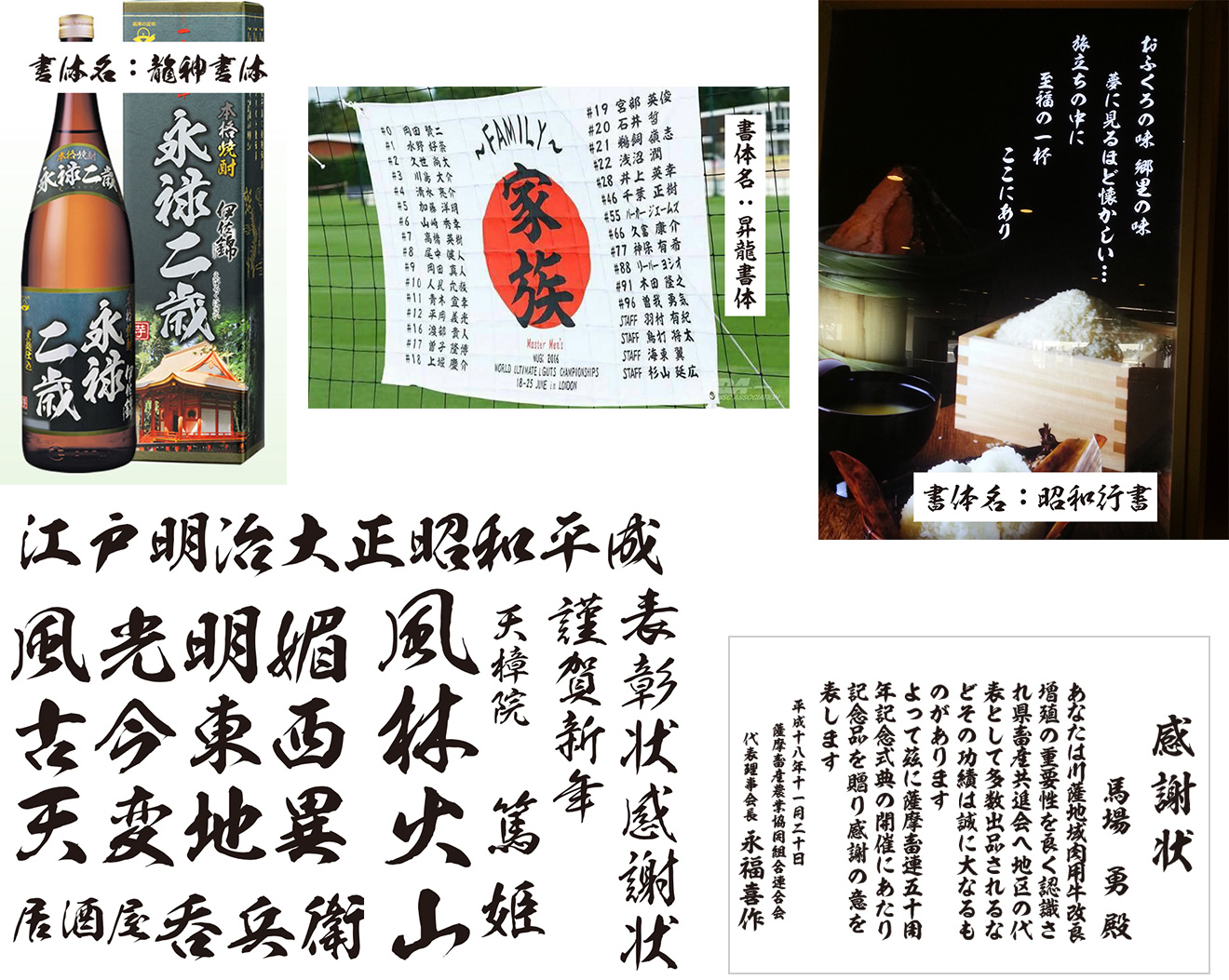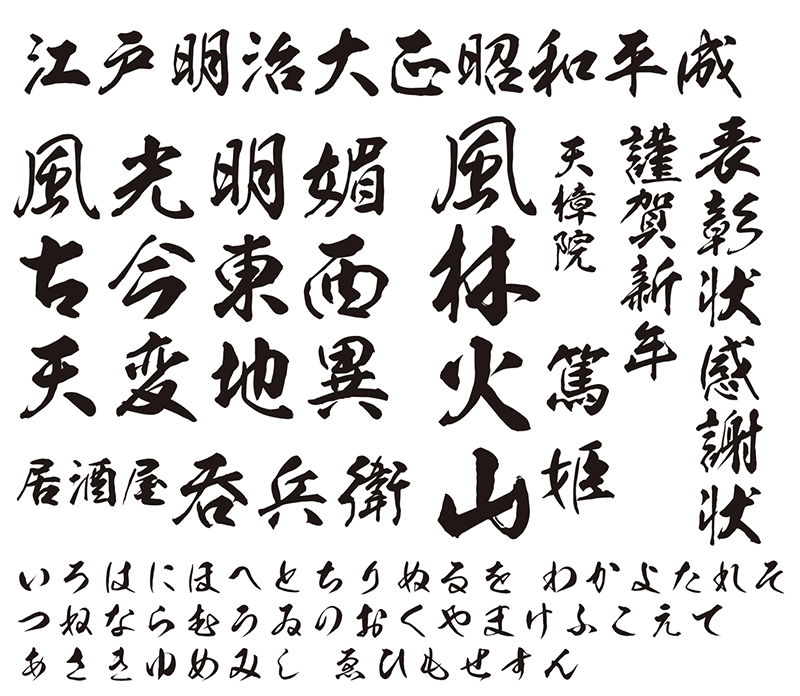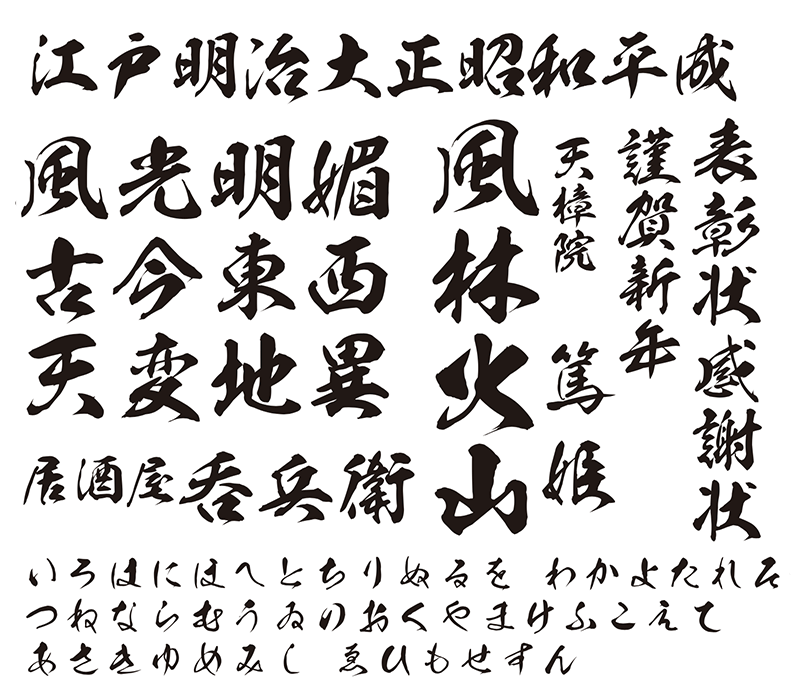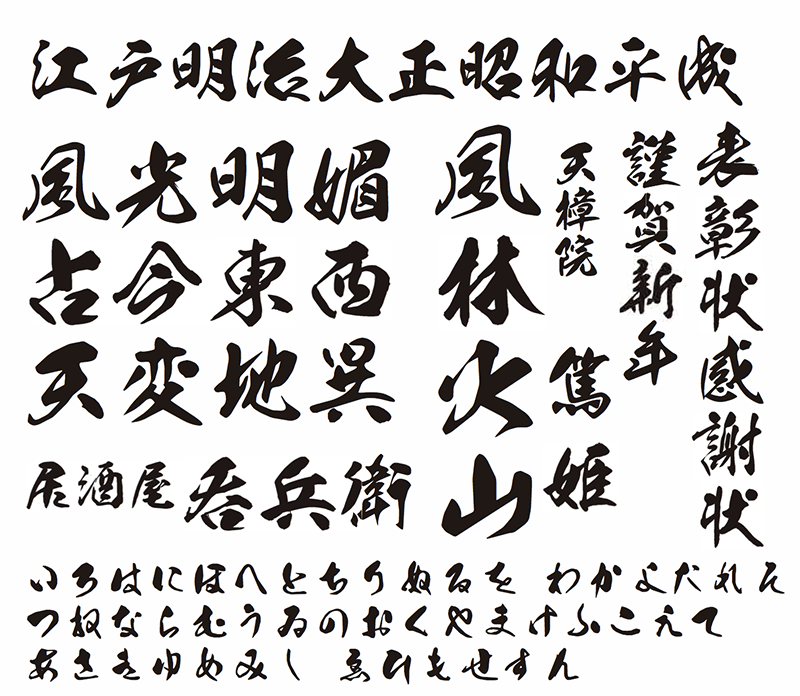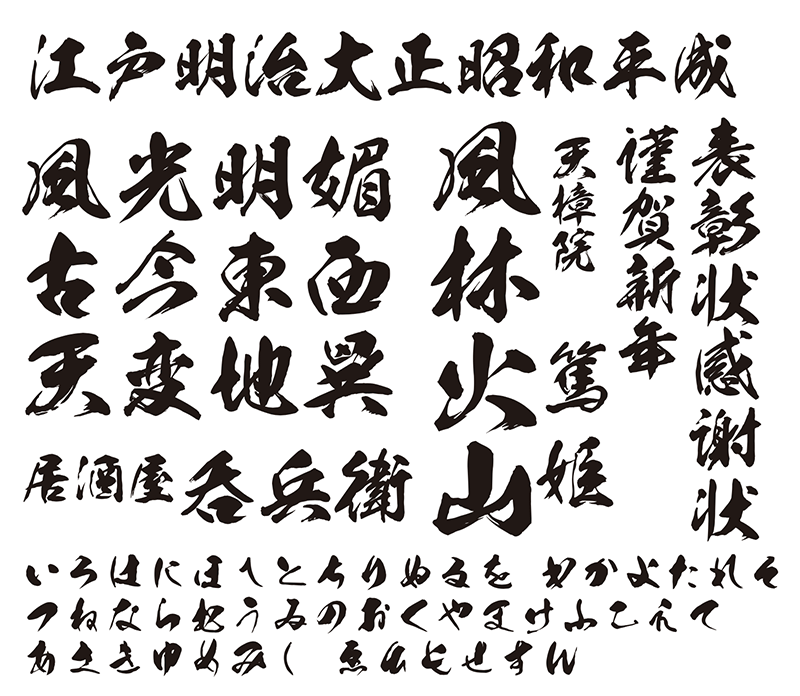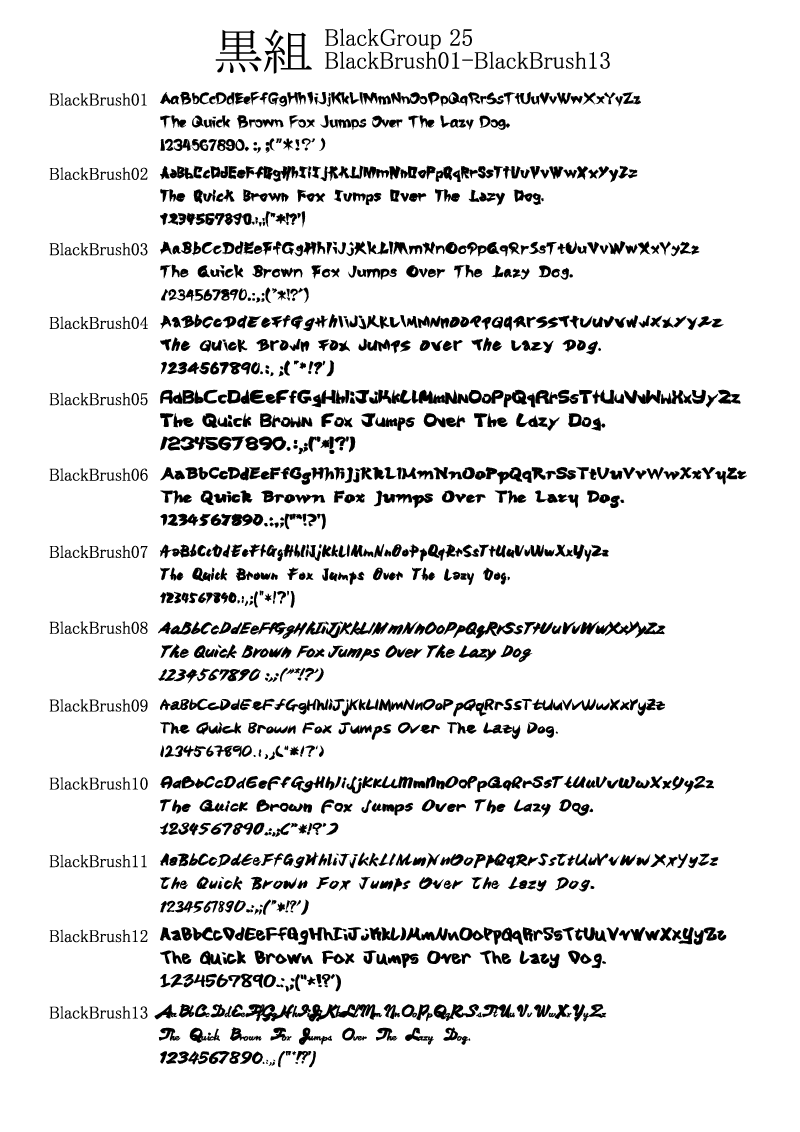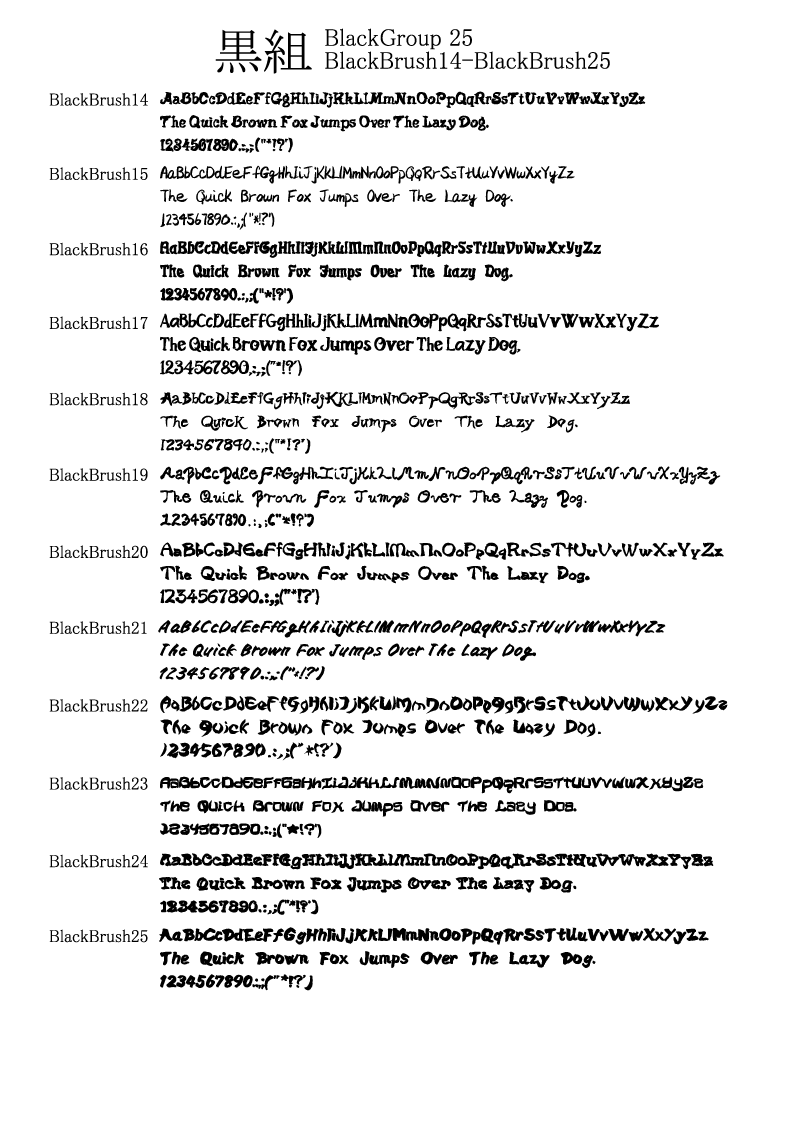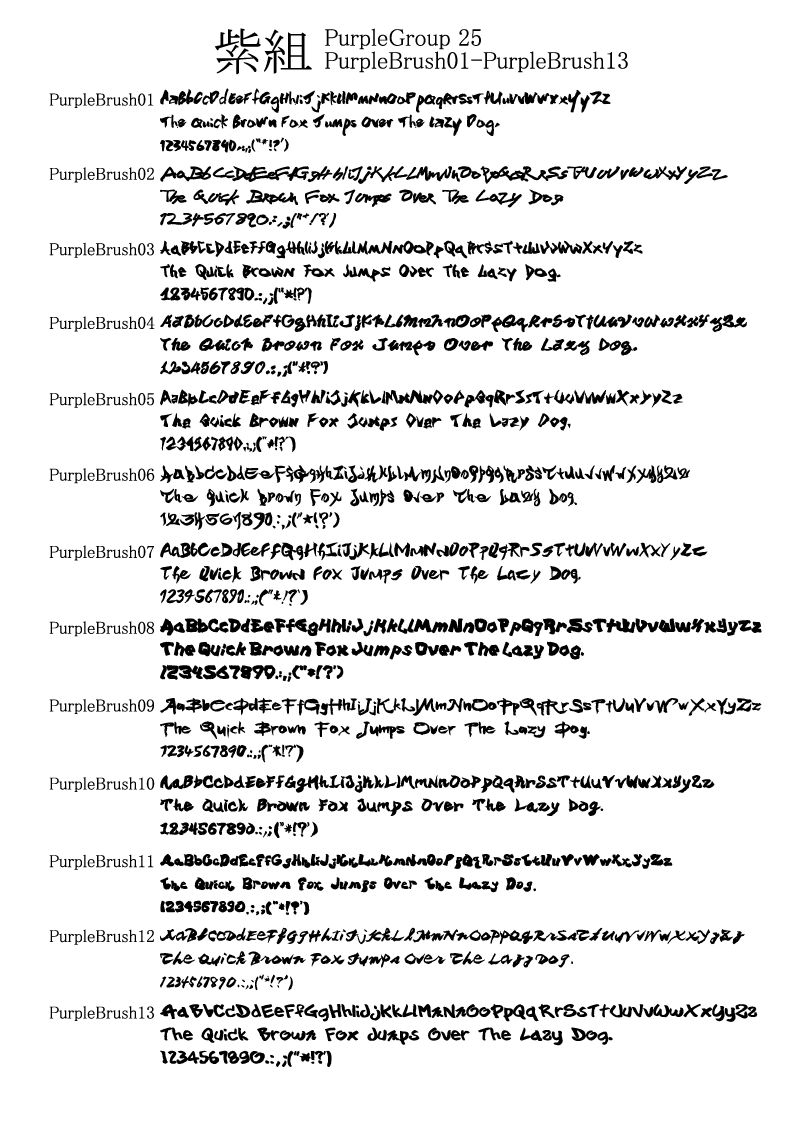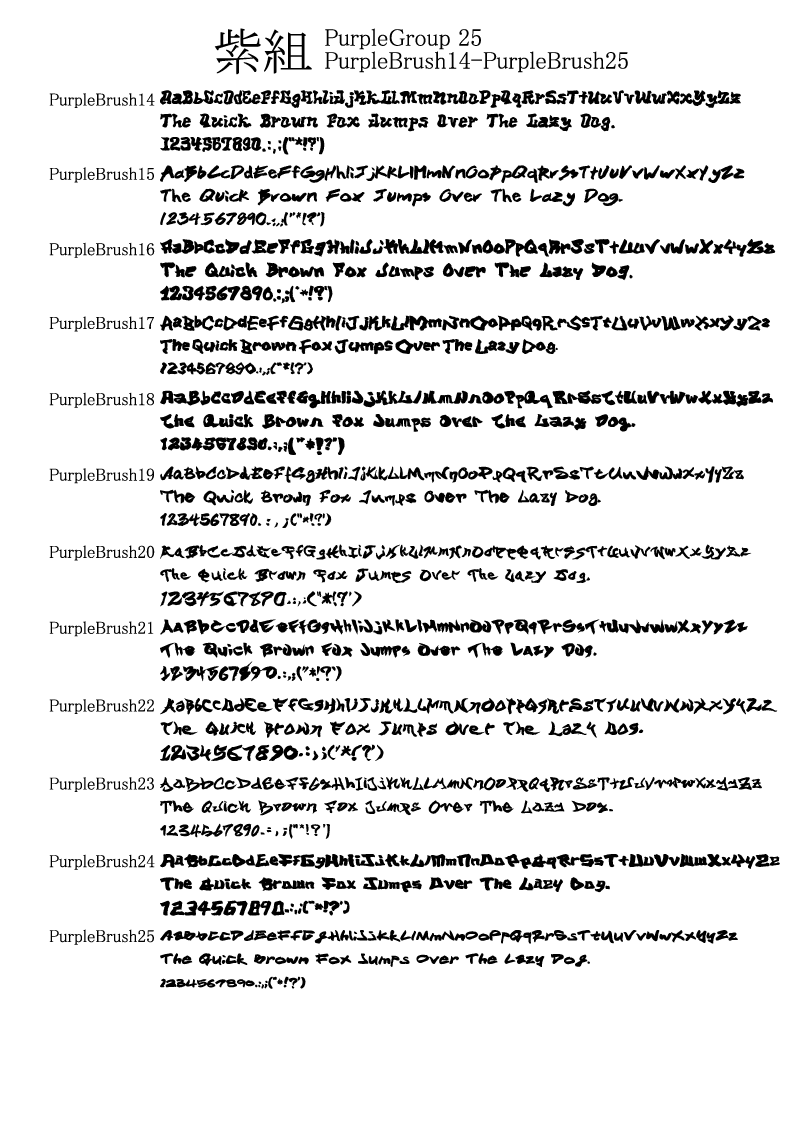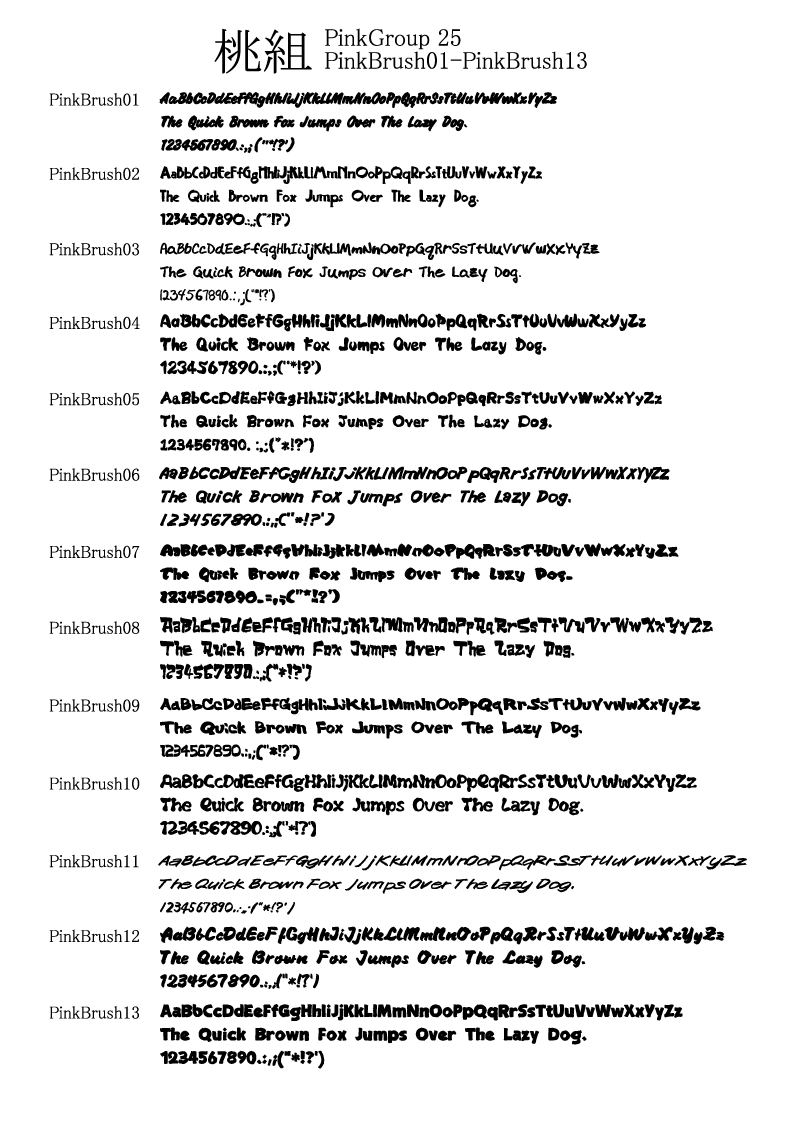
あの人気の筆文字ブランドの昭和書体がFANセレクションシリーズとして製品化。
昭和書体セレクト
昭和書体の基本9書体から2書体をセレクト利用できます。(※クリックで拡大)
昭和楷書スタンダードな毛筆楷書
昭和行書スタンダードな毛筆行書
風神女性的なデザイン毛筆書体
雷神男性的なデザイン毛筆書体
龍神荒々しい龍を彷彿とさせる書体
清龍手紙など文章を作成するにふさわしい毛筆書体
花神ひなびた村に咲く一本の古桜を思わせる優しい毛筆書体
新太楷書名のごとく太めの毛筆書体
昇龍正楷書に近いオリジナルの毛筆書体
BRUSH FONT 99
昭和書体シリーズの欧文フォントを99書体収録。(※クリックで拡大)